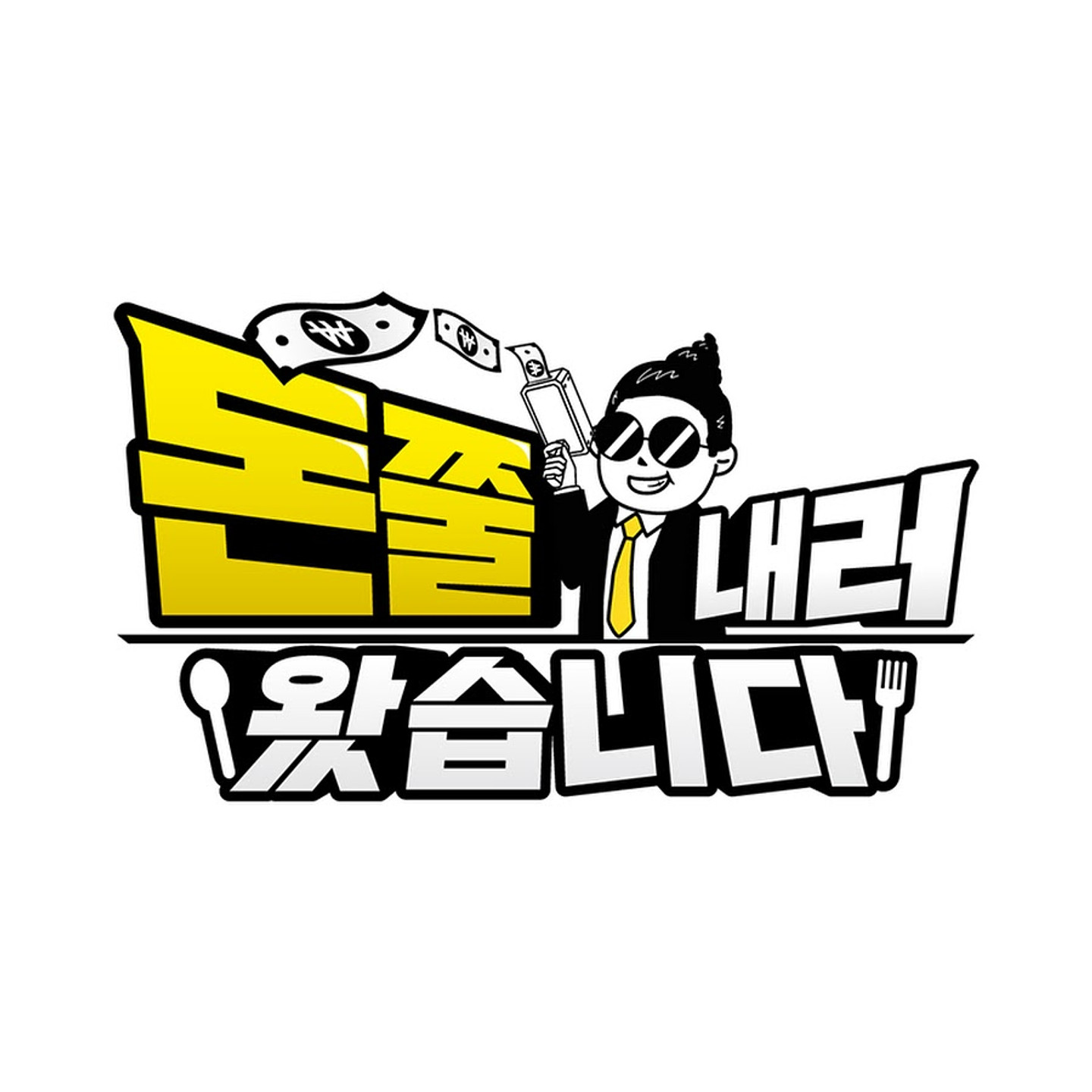
KoreanRKTR Regular
KoreanRKTR Regular 이게 그나마 좀 비슷해보입니다
Sandoll 시네마극장
을 기반으로 변형을 줬네요. https://www.sandollcloud.com/font/224.html KoreanRKTR는 모든 세로획에 변형을 주기 때문에 틀렸고 시네마극장이 맞습니다.
KoreanRKTR Regular